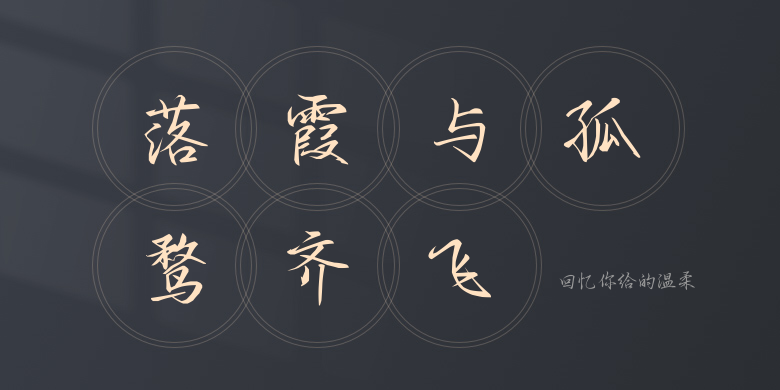
回忆你给的温柔
回忆你给的温柔,这款字体结构工整、笔画清晰,兼顾美观与易读性,适用于标题、正文、海报、包装、LOGO 等多种场景。字形优雅稳定,风格百搭耐看,适配日常排版与创意设计,让文字呈现更舒适、更具质感。回忆你给的温柔一笔一画,皆是细节,以均衡的比例、流畅的线条打造舒适视觉体验,字形端正大气,风格简约现代。无论是商业设计、品牌宣传还是日常排版,都能轻松驾驭,让文字更有格调与力量。回忆你给的温柔字体下载。